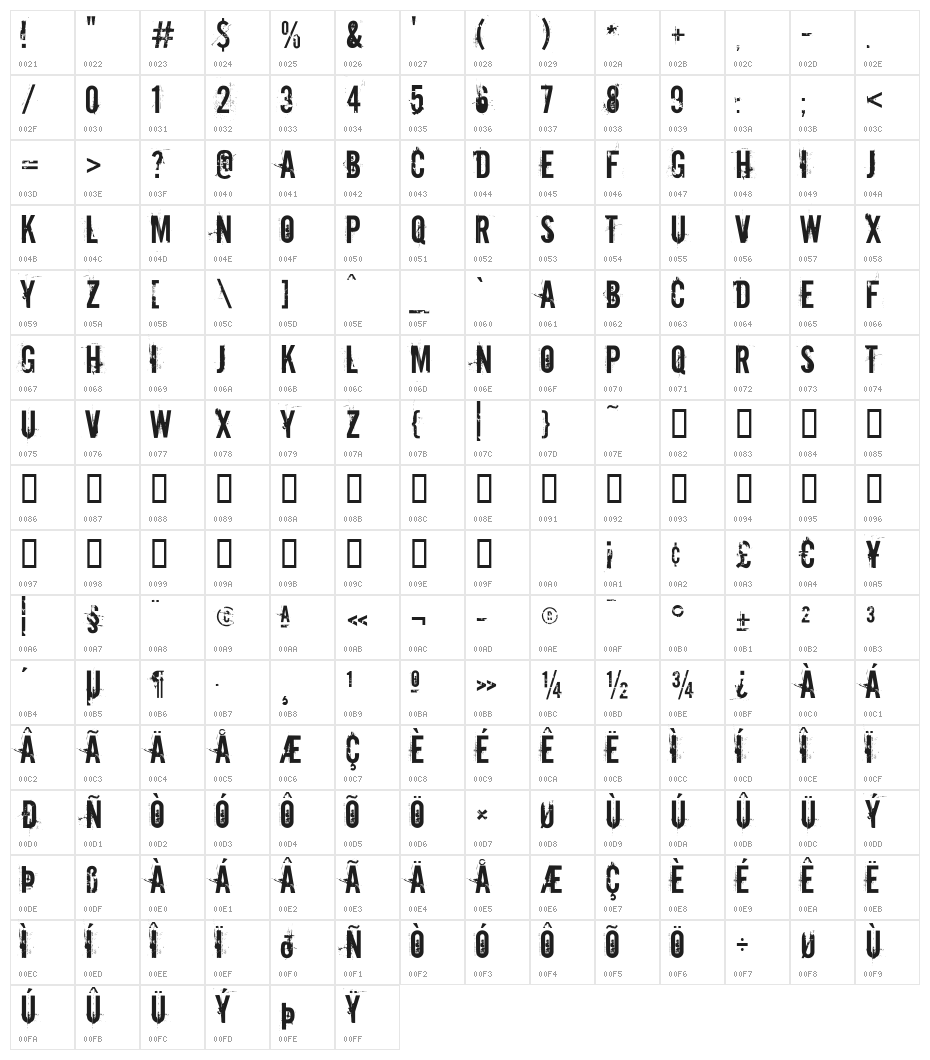
Downcome Font
✎ Distorted Eroded
| Kategorien | Distorted Eroded |
| Gesamtstil | Vintage |
| Vorgeschlagene Projekte | Ideal for posters, album covers, branding for edgy or vintage-themed products, and any design needing a bold, impactful look. |